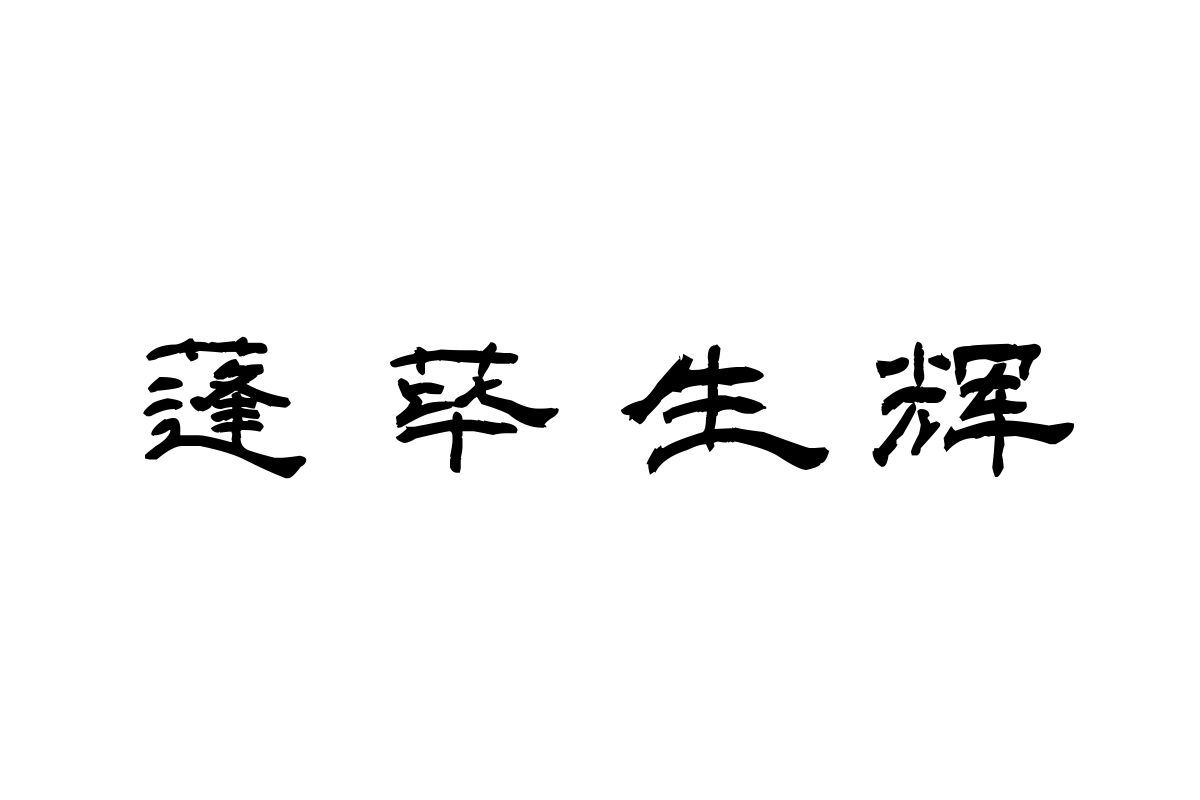
汉呈波波魅隶体是一款具有独特风格的汉字字体,它融合了现代与古典的元素,将传统隶书的笔触与现代设计的简洁线条相结合。这种独特的设计风格使得汉呈波波魅隶体在视觉上呈现出一种既有力量又不失柔美的效果。
该字体的特点包括:
– 笔画流畅而有力,展现出隶书的古朴韵味;
– 结构紧凑,每个字都显得饱满而有张力;
– 字形大小适中,适合各种应用场景,如标题、正文等;
– 色彩丰富,可以用于各种颜色背景,增加视觉效果;
– 易于识别,适用于商业广告、海报、书籍封面等多种设计场合。